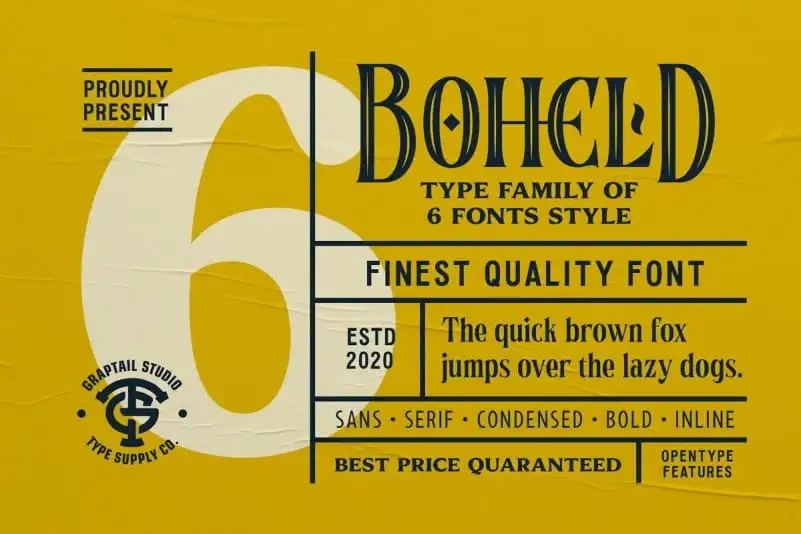
Boheld Serif Font
A fonte ‘Boheld Serif’ é uma elegante tipografia serifada para apresentações luxuosas e majestosas, criada pelo designer Graptail na plataforma 99designs. Boheld Serif oferece um tipo com contração de letras marcantes que captura o glamour e a majestade. Este design exibido em alta contraste é ideal para criações de artigos de luxo como etiquetas e cartazes, inspirando criatividade instantaneamente. Boheld Fonts Collection traz uma gama impressionante de 6 diferentes variações do tipo, incluindo Sans, Serif, Bold, Condensed e Inline. Inspirado em elementos tradicionais como rótulos, bilhetes e cartazes, Boheld é perfeito para os criadores que desejam agregar um toque elegante a seus projetos. Com a ‘Boheld’ no seu arsenal de tipos, você pode criar obras que expressam elegância e sofisticação sem igual. Não hesite em explorar o vasto potencial da Boheld Serif Collection; ela oferece um preço justo para qualidade impecável, pronta para ser sua escolha de tipo preferida.